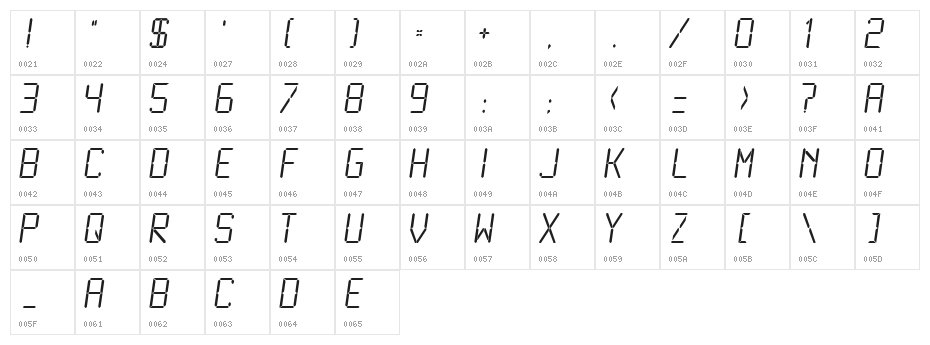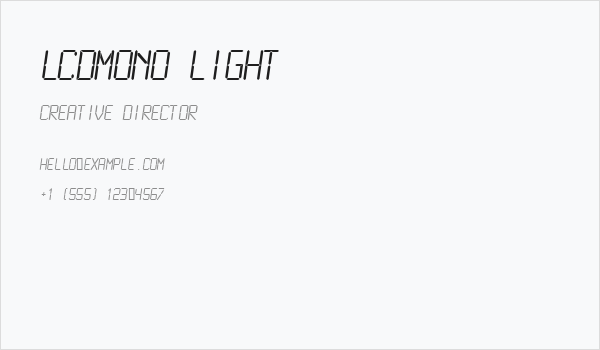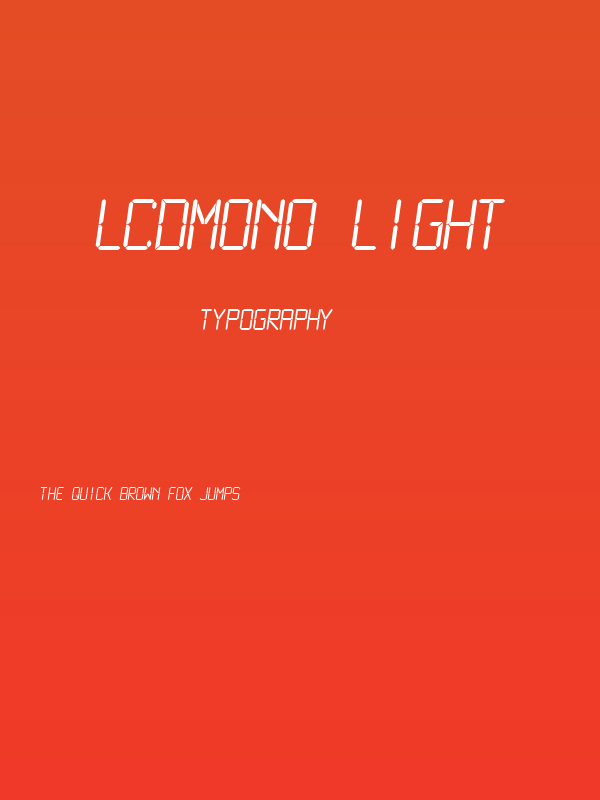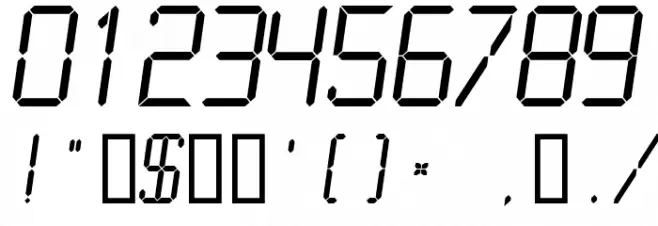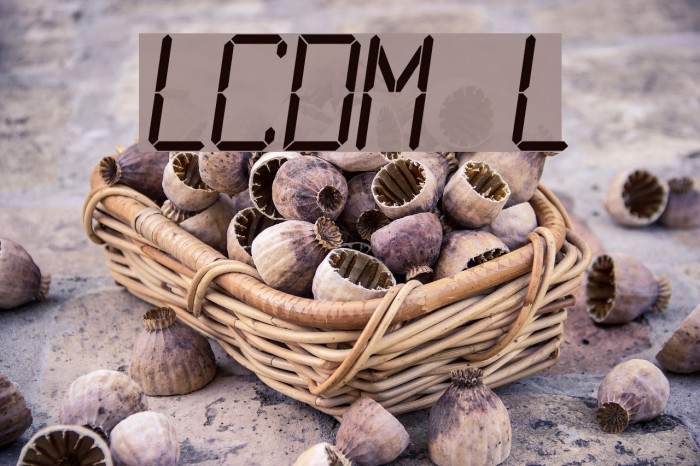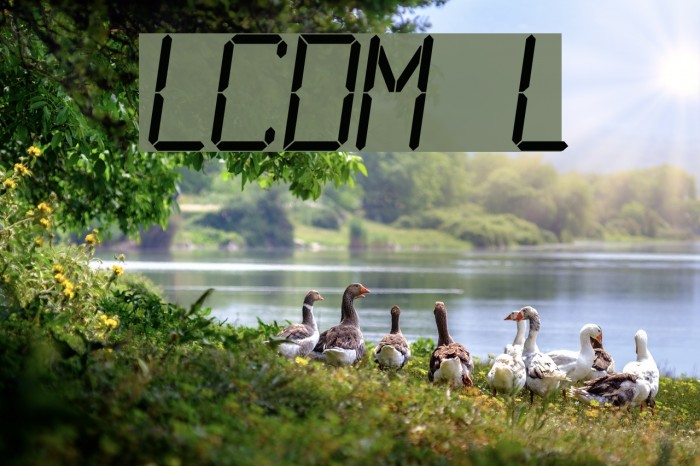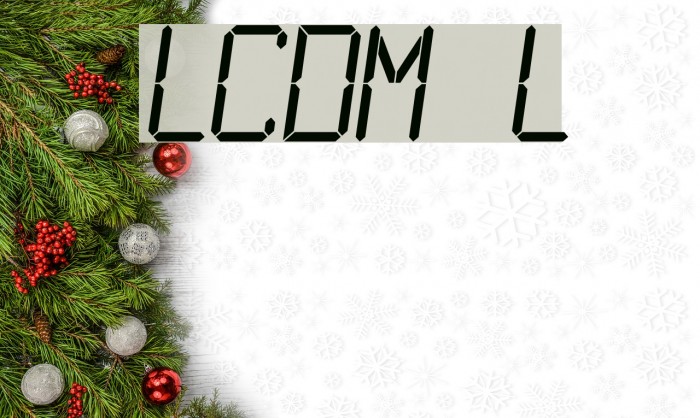
LCDMono Light Font
| Caso d'uso | Digital displays, tech interfaces, coding, retro designs. |
| Progetti proposti | Ideal for digital interfaces, tech-themed designs, coding environments, and retro-futuristic projects. |